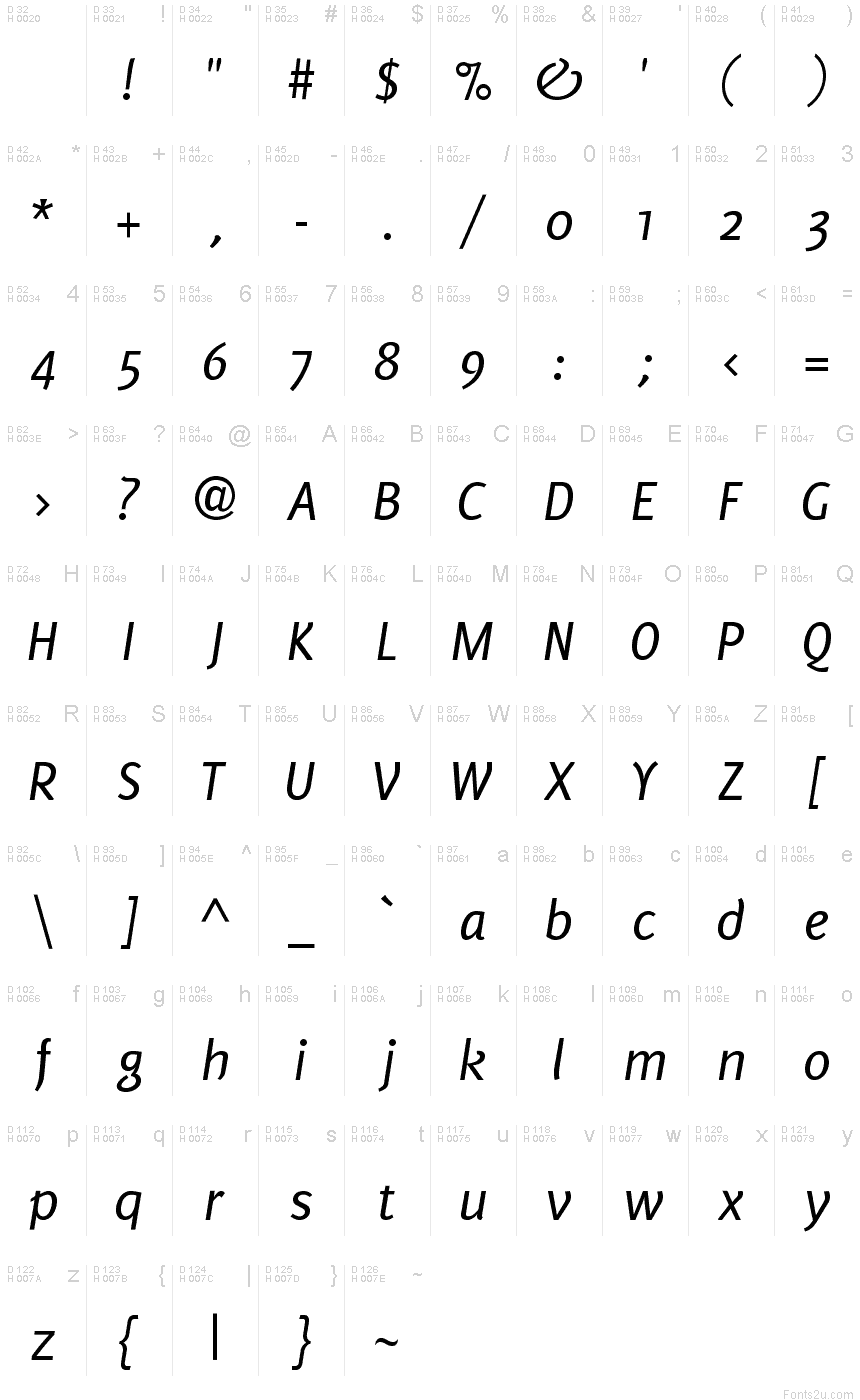
Delicious Italic von Jos Buivenga ist eine kostenlose humanistische Kursiv-Sans-Serif mit fließenden, leicht kalligrafischen Buchstabenformen. Ihre geneigten Buchstaben kombinieren geschwungene Bögen mit weich auslaufenden Strichen, was den Formen mehr Wärme verleiht als eine mechanische Schräge. Die Laufweite wirkt offen und die Silhouetten bleiben klar.
Unabhängige Food- und Lifestyle-Marken könnten sie nutzen, um eine zugängliche redaktionelle Identität zu schaffen. Sie eignet sich zudem für Café-Verpackungen, Magazin-Coverzeilen und Event-Poster, bei denen die fließenden Formen Fotografie oder scharfe geometrische Grafiken auflockern können. Der handschriftliche Einschlag passt besonders gut zu Speisekarten und kulinarischen Publikationen und verbindet das Schriftbild mit persönlichen Notizen und Rezepten.